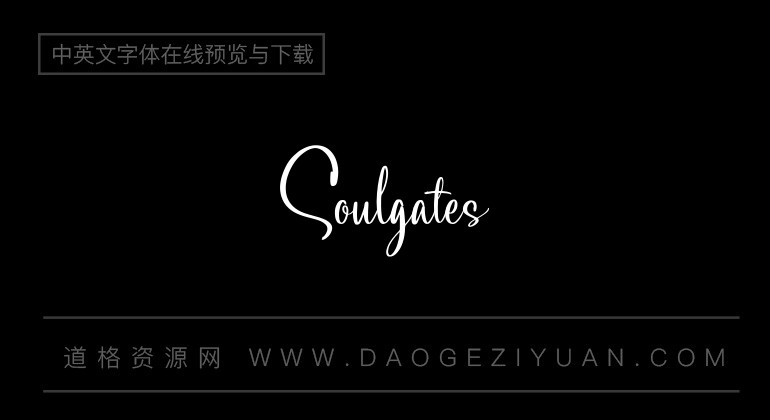
Soulgates
Soulgates 是一款精致的字体,它的特点是细腻、优雅、灵动。字体的轮廓线条精细,字体的笔画有着明显的弧度,使得字体看起来更加柔和,适合用于精致的排版和设计。Soulgates 字体拥有多种字重,可以满足不同的设计需求。它可以搭配多种字体,使用在不同的设计中,比如品牌标志、海报、书籍封面等等,都能发挥出它优雅的特性。
Soulgates是一款非常不错的手写艺术字体,具有很好的视觉感,适合于文化类的宣传设计、商业类品牌的广告和产品包装设计以及个性化文字排版等较多场景。